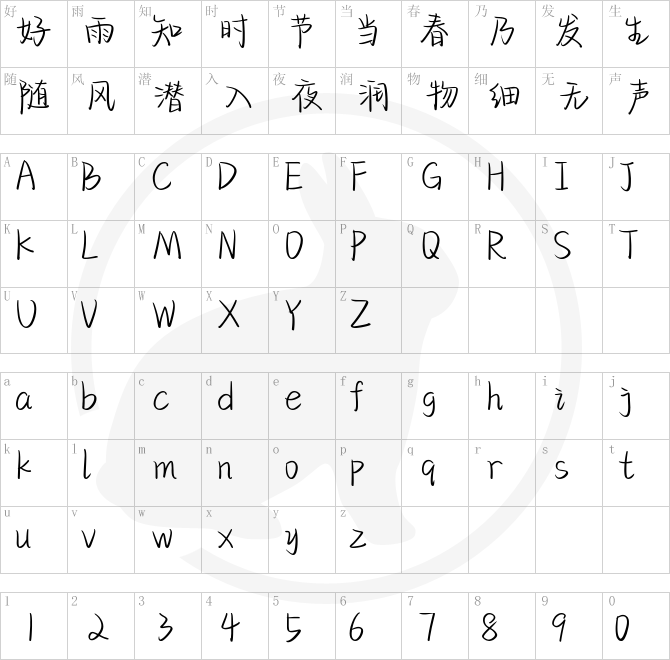
也字工厂雨眠手迹
也字工厂雨眠手迹,这款字体结构工整、笔画清晰,兼顾美观与易读性,适用于标题、正文、海报、包装、LOGO 等多种场景。字形优雅稳定,风格百搭耐看,适配日常排版与创意设计,让文字呈现更舒适、更具质感。也字工厂雨眠手迹一笔一画,皆是细节,以均衡的比例、流畅的线条打造舒适视觉体验,字形端正大气,风格简约现代。无论是商业设计、品牌宣传还是日常排版,都能轻松驾驭,让文字更有格调与力量。也字工厂雨眠手迹字体下载。